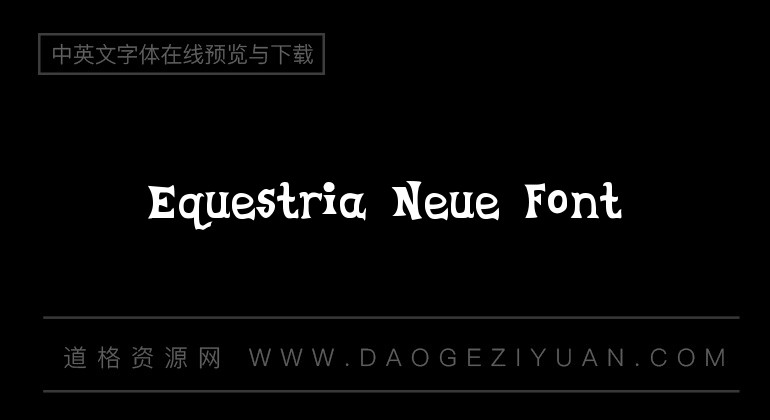
Equestria Neue是一种漂亮的手写风格字体,灵感来自于在迪斯尼电视节目“我的小马驹:友谊就是魔法”中使用的Equestria手写字体。这个新字体具有更多的细节和更加现代化的外观,使其适合于广泛的应用,包括印刷和数字媒体。 Equestria Neue字体具有良好的可读性和清晰度,即使在小字号下也能够清晰可辨。这个字体提供多种字重和字型,包括正常、中等、加粗和斜体,以满足不同设计需求。Equestria Neue字体也支持多种语言,包括英语、西班牙语、法语、德语、意大利语、荷兰语、葡萄牙语等。 总体而言,Equestria Neue字体是一种优雅而现代的手写字体,非常适合在各种印刷和数字应用中使用。内容介绍
Equestria Neue Font是一款非常不错的手写艺术字体,具有很好的视觉感,适合于文化类的宣传设计、商业类品牌的广告和产品包装设计以及个性化文字排版等较多场景。